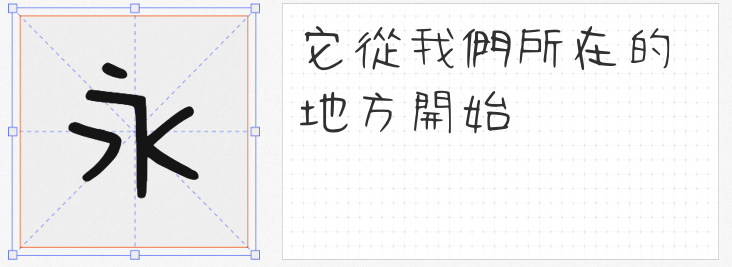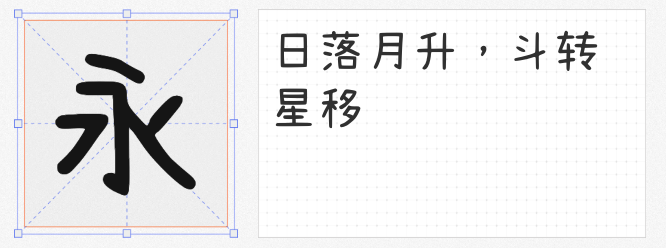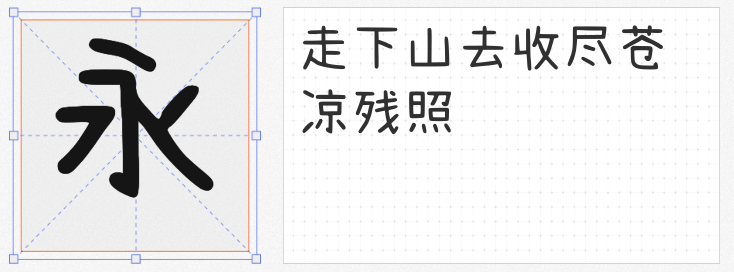
在追求个性化表达的视觉时代,手写字体以其独特的温度感与亲和力,成为品牌设计、社交媒体内容创作的热门选择。本文精选四款风格各异的免费商用可爱手写字体,从自然随性到创意变形,为你的设计注入童趣与活力。
1. 清松手写体8
由游清松先生匠心打造的第八代作品,延续了系列"人性化书写"的核心特质。这款字体摒弃机械规整的笔画,通过微妙的粗细变化与连笔设计,还原真实手写的呼吸感。无论是用于儿童绘本、手账装饰还是文艺类短视频字幕,其不刻意修饰的随性风格都能瞬间拉近与受众的距离,传递温暖治愈的视觉语言。
2. 拾陆字濑户2.0 Regular
基于经典「全濑Pro」升级优化的五字重体系,满足多元场景需求。轻字重版本通过笔画交接处的自然粘连,精准复现水笔书写时的墨水晕染效果,适合制作动态笔触动画;重字重版本则以均匀的粗线条构建圆润可爱的字形结构,尤其适合儿童教育类设计或卡通IP形象开发。设计师可通过字重调节实现从清新到软萌的视觉跨越。
3. 礼品卉自由理想体
这款充满叛逆精神的字体,用"不规矩"重新定义可爱。横竖笔画故意保留书写时的自然抖动,框形结构被趣味圆圈替代,仿佛将"葛优躺"的慵懒姿态转化为视觉符号。在社交媒体表情包、创意海报或互动H5设计中,其打破常规的造型能瞬间制造记忆点,成为年轻群体表达态度的视觉利器。
4. cjkFonts全濑体
通过深度学习技术扩展的濑户字体家族,实现繁简日韩四语种全面覆盖。在保留原版手写韵味的基础上,智能优化了东亚文字共通的结构特征,使多语言排版保持视觉统一。对于需要制作双语儿童读物或跨国品牌周边的设计师而言,这款字体既保证了可爱风格的一致性,又大幅提升了多语言设计的效率。
这四款字体通过差异化设计语言,构建起从基础应用到创意表达的完整可爱体系。无论是追求自然书写的温度感、需要多语言支持的实用性,还是渴望突破常规的趣味性,都能在这份清单中找到理想解决方案。让设计回归人性本真,从选择一款有温度的手写字体开始。